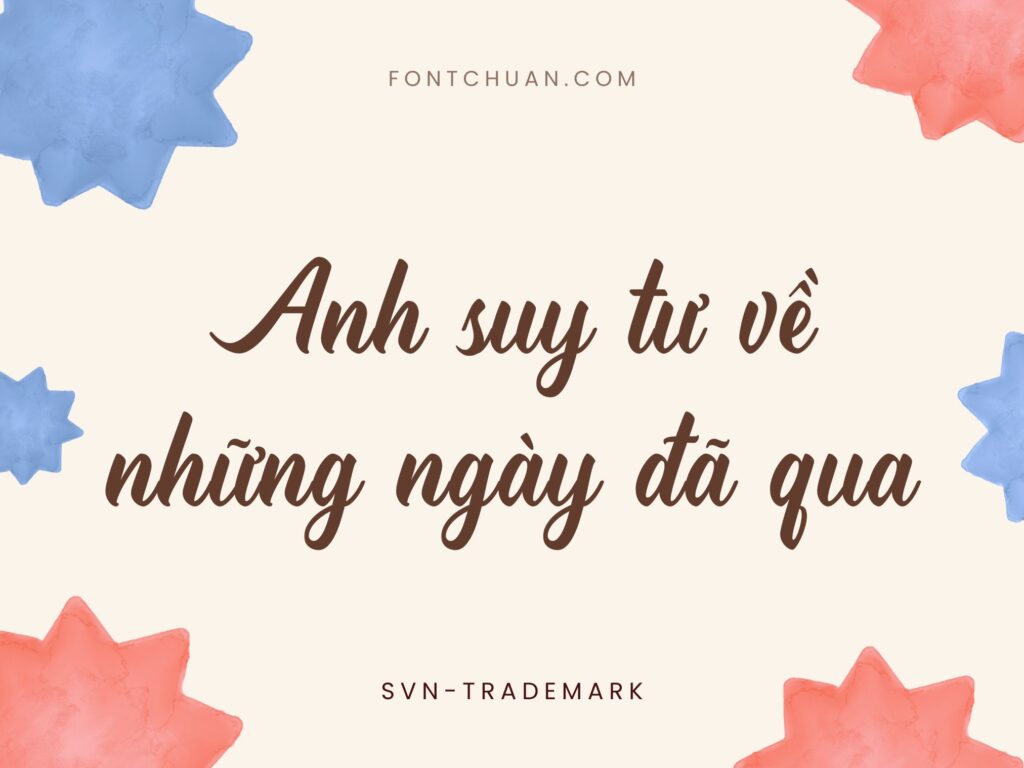
Font SVN Trademark Việt Hóa
Font SVN TradeMark là phiên bản Việt hóa của kiểu chữ TradeMark, được thực hiện bởi STYLEno.1 Fonts. TradeMark là một kiểu chữ script được thiết kế bởi Zoeljroh và phát hành qua Jroh Creative Type Foundry. Font này được tạo ra nhằm hỗ trợ thiết kế thương hiệu, logo, biển hiệu, bao bì sản phẩm, tiêu đề, áo thun và các ấn phẩm đồ họa khác. TradeMark bao gồm các định dạng OTF, TTF, webfont và kèm theo mẫu logo miễn phí. Phiên bản Việt hóa được cung cấp miễn phí cho mục đích sử dụng cá nhân. ([svnfont.com](https://www.svnfont.com/viet-hoa-svn-trademark/))
SVN TradeMark lý tưởng cho các dự án thiết kế yêu cầu sự sáng tạo và cá nhân hóa, như thiết kế logo, tiêu đề, bao bì sản phẩm và các ấn phẩm truyền thông. Các ngành nghề như quảng cáo, thiệp cưới và spa có thể tận dụng font này để tạo điểm nhấn trong thiết kế. Ngoài ra, font cũng thích hợp cho các sự kiện như Tết, Valentine, Sinh nhật và các lễ hội khác.